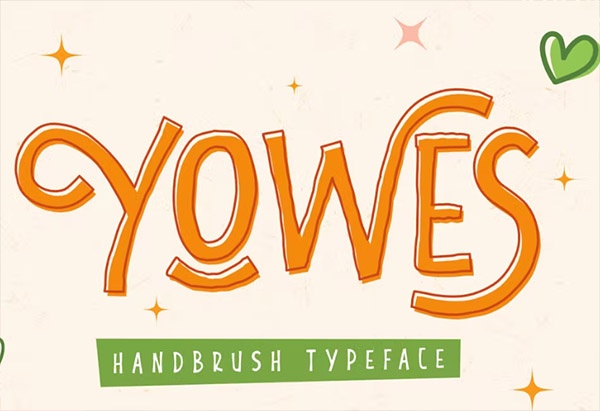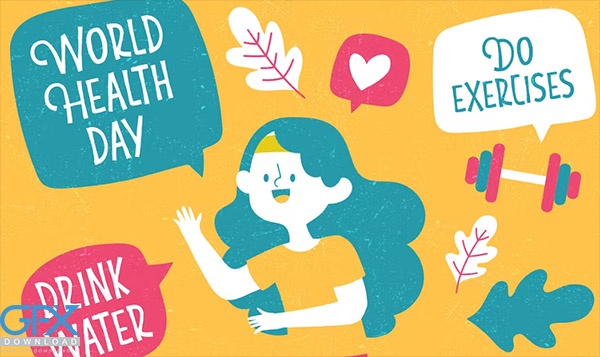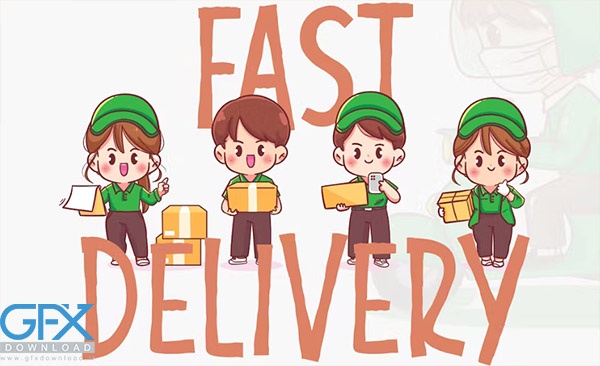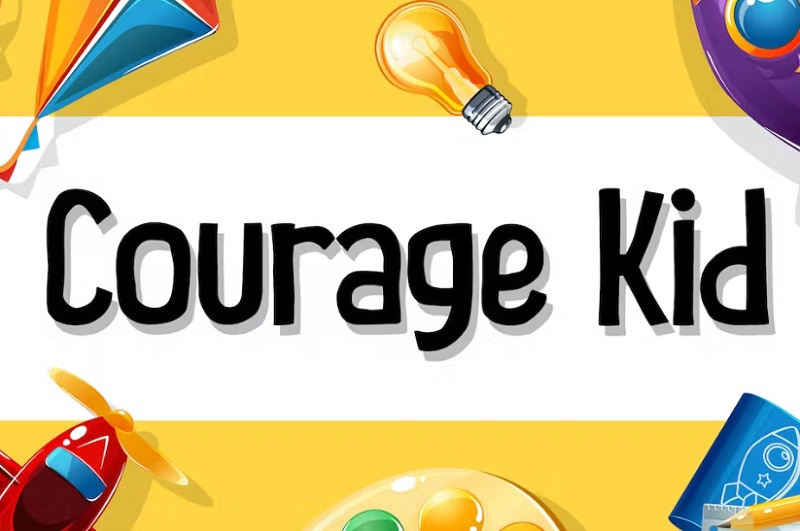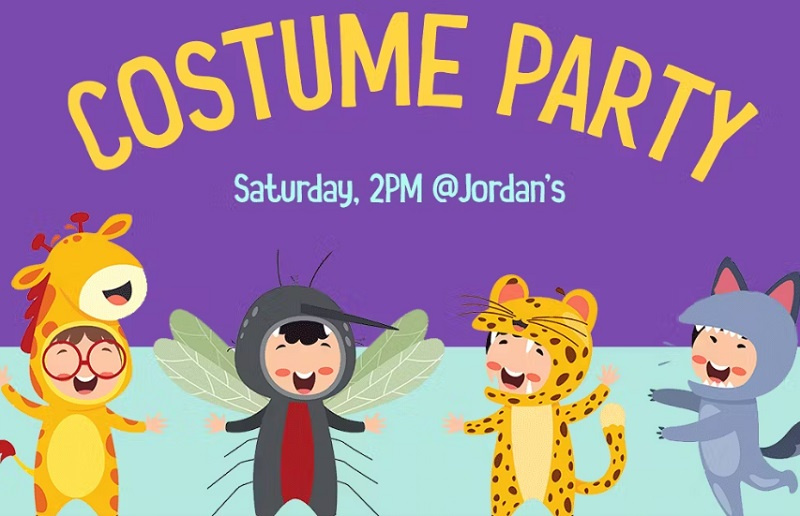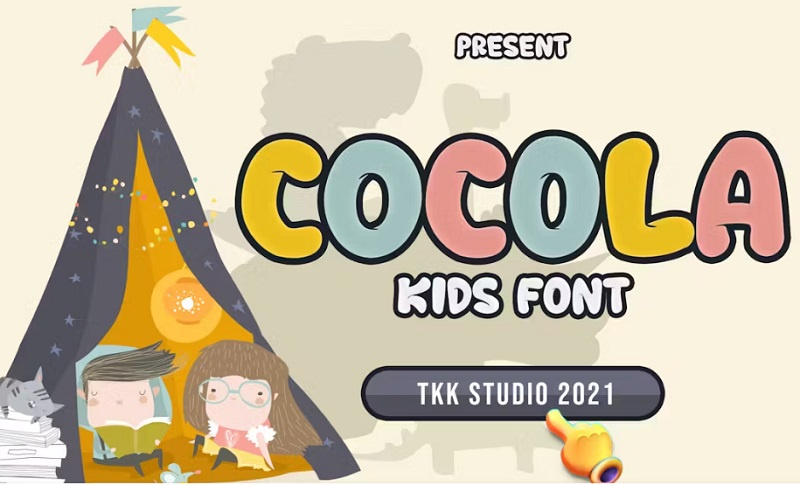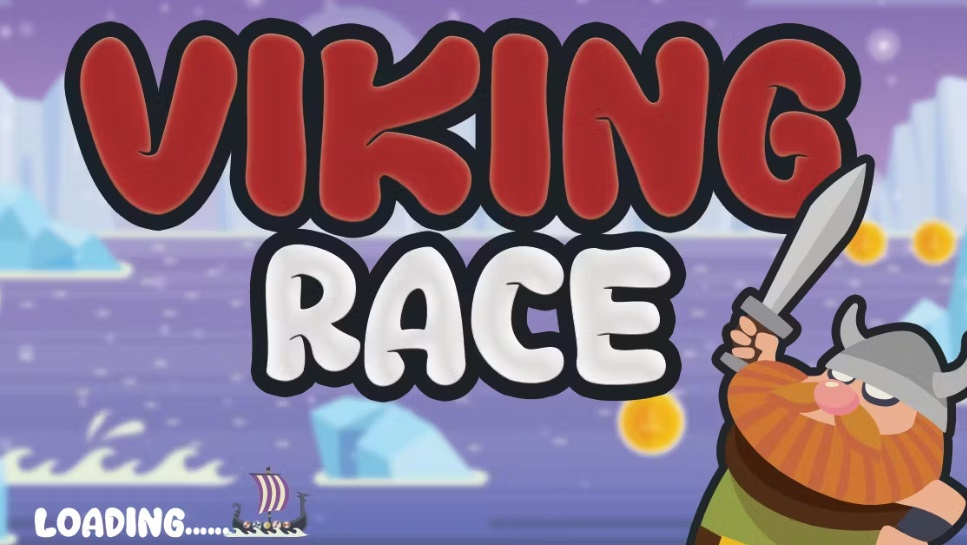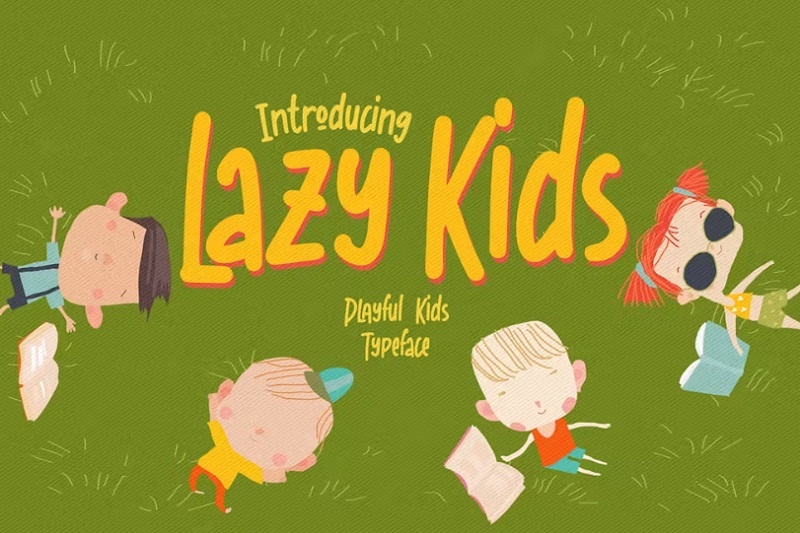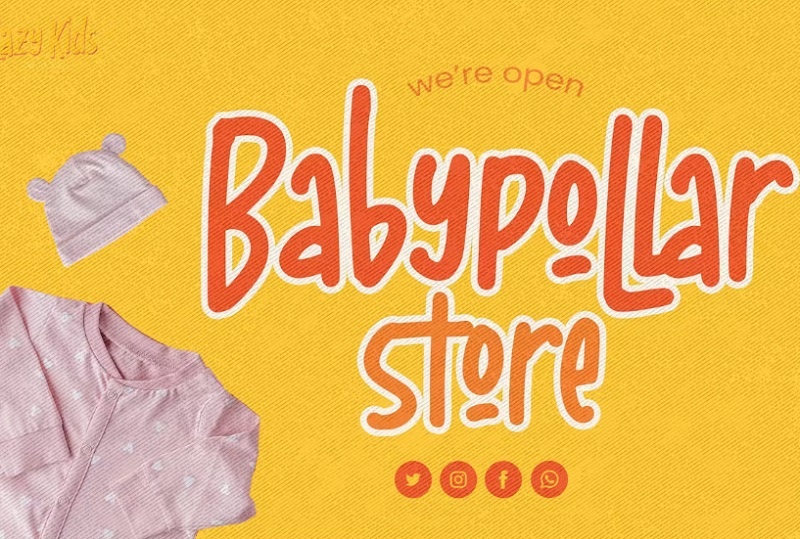
دانلود فونت انگلیسی کودکانه Yowes Fun Kids آپدیت 2024
فونت انگلیسی کودکانه از جی اف ایکس دانلود. این مجموعه شامل 4 فونت کودکانه انگیسی شاد و رنگارنگ می باشد. این فونت ها با طراحی کودکانه و جذاب برای طراحی های کودکانه، فانتزی، محصول، سرگرمی و ... مناسب است. این فونت انگلیسی کودکانه و در عین حال زیبا است که برای نمایش هر محصول، محتوای رسانههای اجتماعی، یوتیوب برای عناوین ویدیوی کودکان یا جلد کتاب کودکان عالی است.
1- دانلود فونت انگلیسی کودکانه Yowes Fun Kids
فونت انگلیسی مخصوص کودکان صرفاً برای هر طرح ساده ای ساخته شده است که حالات شادی را پخش می کند. شامل Yowes (OTF/TTF) حروف استاندارد سبک قلم وب جایگزین Ligature روی کامپیوتر و مک کار می کند، نصب ساده.
COCOLA یک فونت بازی و سرگرمی به سبک کودکانه است، فونت انگلیسی کودکان مناسب برای بازی های آنلاین، پوستر، عنوان فیلم، منوی فست فود، مجله، جلد یوتیوب، تصاویر کوچک یوتیوب. ، جلد صفحات شبکه های اجتماعی و غیره می باشد.
فونت انگلیسی فانتزی کودکانه
Lazy Kids یک فونت کودکانه فانتزی به سبک شاد و بازیگوش می باشد. این فونت کودکانه برای هر پروژه طراحی مانند دعوت نامه، لوگو، جلد کتاب، کاردستی یا هر هدف طراحی دیگر مناسب است. شامل فایل های OTF/TTF می باشد.